‘카페 이마’ 리뉴얼 : 새롭게 그러나 생경하지 않게
광화문 일민미술관에 위치한 ‘카페 이마’를 아는가? 햄버그스테이크와 와플로 유명했던 이곳이 이제는 또 하나의 예술 공간으로도 자리 매김하게 될 것 같다. 최근 공간을 리뉴얼하며 디자이너 혹은 예술가가 이마의 공간을 활용해 작업을 선보이는 프로젝트가 기획되었고, 메뉴와 로고, 사인 리뉴얼 등을 이미 의뢰받아 진행 중이던 디자이너 듀오 홍은주, 김형재가 첫 번째 협업자로서 작업을 선보였기 때문이다.
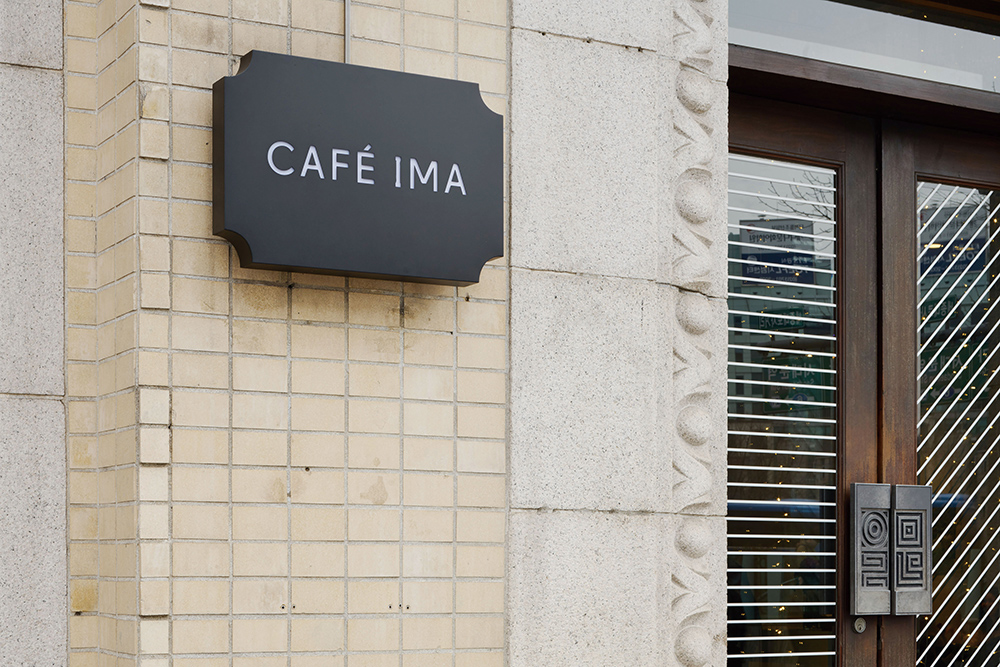
카페 이마
“카페 이마는 이번 리뉴얼에 있어 완전한 교체보다는 기존안을 개선하는 점진적 방식을 원했습니다. 그래서 아이덴티티의 경우 산세리프 서체를 유지하되 보다 최근에 만들어져 친밀감이 드는 서체로 교체하는 방향을 제안했습니다. 푸가(FUGUE)를 택했는데요, 이 서체를 디자인한 라딤 페슈코(RADIM PESKO)가 밝히는 대로 이 디자인이 파울 레너(PAUL RENNER)의 기하학적 서체 디자인의 유산과 미래주의로의 복고 등과 관련 있는 점도 좋아했고 특히 몇몇 대문자 글자들을 무척 좋아했기 때문입니다. 이 서체가 친밀하면서도 새로운 느낌을 줄 수 있을 것이라 생각했고 물론 모든 중요한 텍스트는 대문자로만 사용하기로 했습니다.”
새로 바뀐 카페 이마의 아이덴티티 작업 과정에 관해 홍은주가 이야기한다.
카페 이마 내부
공간 그래픽 작업에 접근할 때엔 유서 깊은 건물에 위치한 이마의 클래식한 인상을 살리는 동시에 푸가로 쓰인 어느 정도 레트로-모던한 형태의 로고와 어울리게 네 가지 형태의 몇 가지 기본적인 오브젝트를 디자인했다. 이후 이 오브젝트들이 연관된 선이나 점으로 그려진 음영 패턴들을 다시 만들어 여러 공간의 면에 다양하게 조합해 적용할 수 있는 시스템을 제안했다. 아이덴티티에 사용된 그래픽들이 입체가 되어 공간 안에 설치되는 것이 중요 컨셉이었기 때문이다.
“만화에서 그림자 부분에 스크린톤을 붙여 넣는 것처럼 실제로 기둥의 뒷면이나 보의 측 등 그림자가 드리울 만한 부분들에 패턴을 채워 넣었습니다. 아이덴티티의 일부인 네 가지 도형은 각각 조명과 거울 등 서로 다른 재질과 특성의 입체 조형물로 바뀌어 공간 벽면에 설치되었고요.”
카페 이마 내부